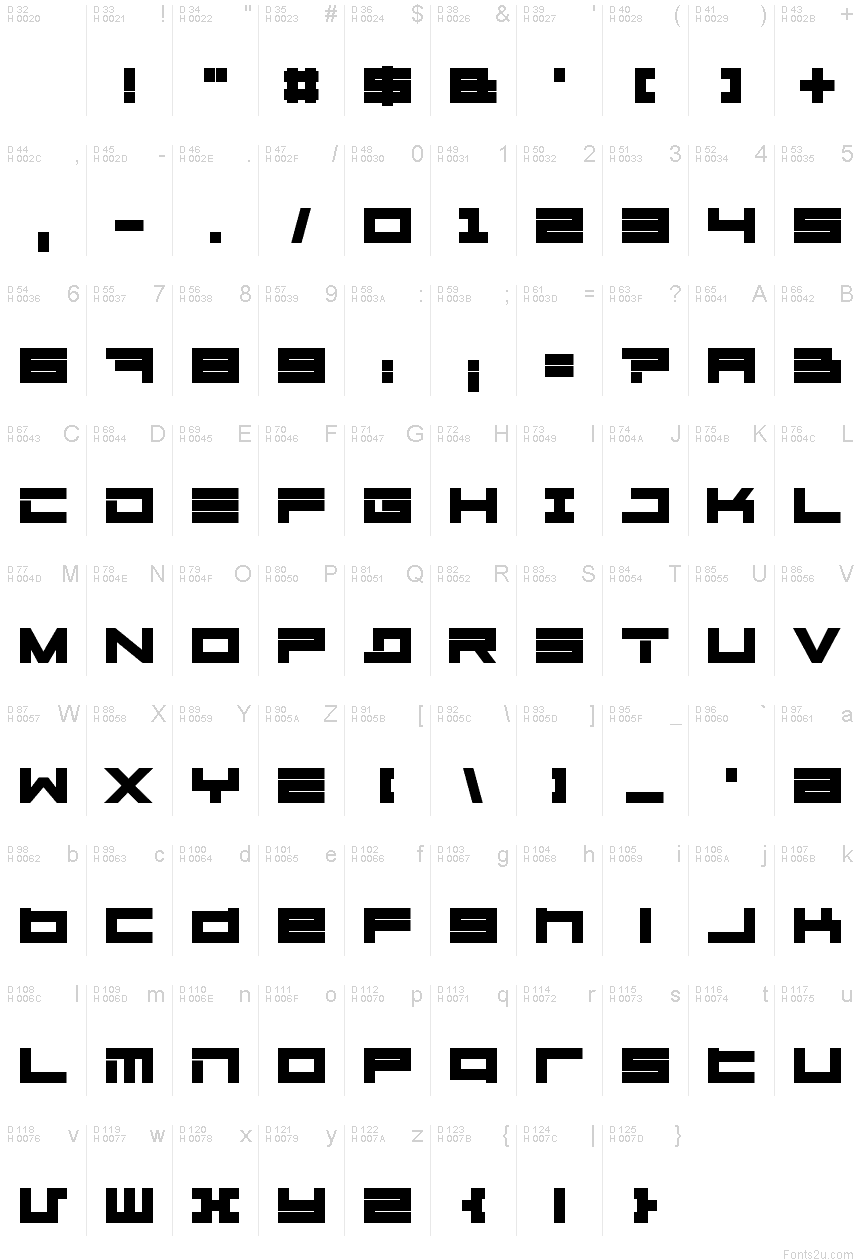
Megaton Extras Heavy
Megaton Extras Heavy od dustBUST Fonts to darmowy techniczny font typu display o kwadratowej, segmentowanej strukturze z otwartymi przerwami wewnątrz liter. Powtarzające się paski i wycięte bloki nadają mu mechaniczny rytm, dzięki czemu rodzina fontów sprawia wrażenie zestawu złożonych elementów, a nie jednego, płynnego zarysu.
Megaton Extras Heavy świetnie sprawdzi się w logo, nagłówkach plakatów, tytułach w stylu arcade, opakowaniach sci-fi oraz ulotkach eventowych, które wymagają zakodowanego, inżynieryjnego charakteru. Jego sztywna geometria sprawdza się zwłaszcza w krótkich tekstach, gdzie kanciaste formy niosą cały projekt bez potrzeby dodatkowych zdobień.